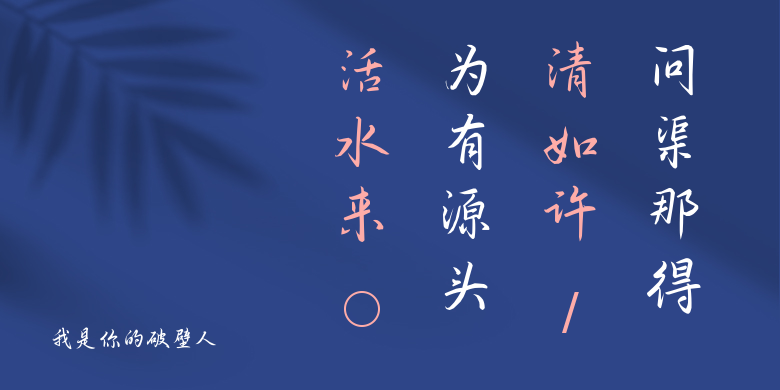
我是你的破壁人
我是你的破壁人,这款字体结构工整、笔画清晰,兼顾美观与易读性,适用于标题、正文、海报、包装、LOGO 等多种场景。字形优雅稳定,风格百搭耐看,适配日常排版与创意设计,让文字呈现更舒适、更具质感。我是你的破壁人一笔一画,皆是细节,以均衡的比例、流畅的线条打造舒适视觉体验,字形端正大气,风格简约现代。无论是商业设计、品牌宣传还是日常排版,都能轻松驾驭,让文字更有格调与力量。我是你的破壁人字体下载。